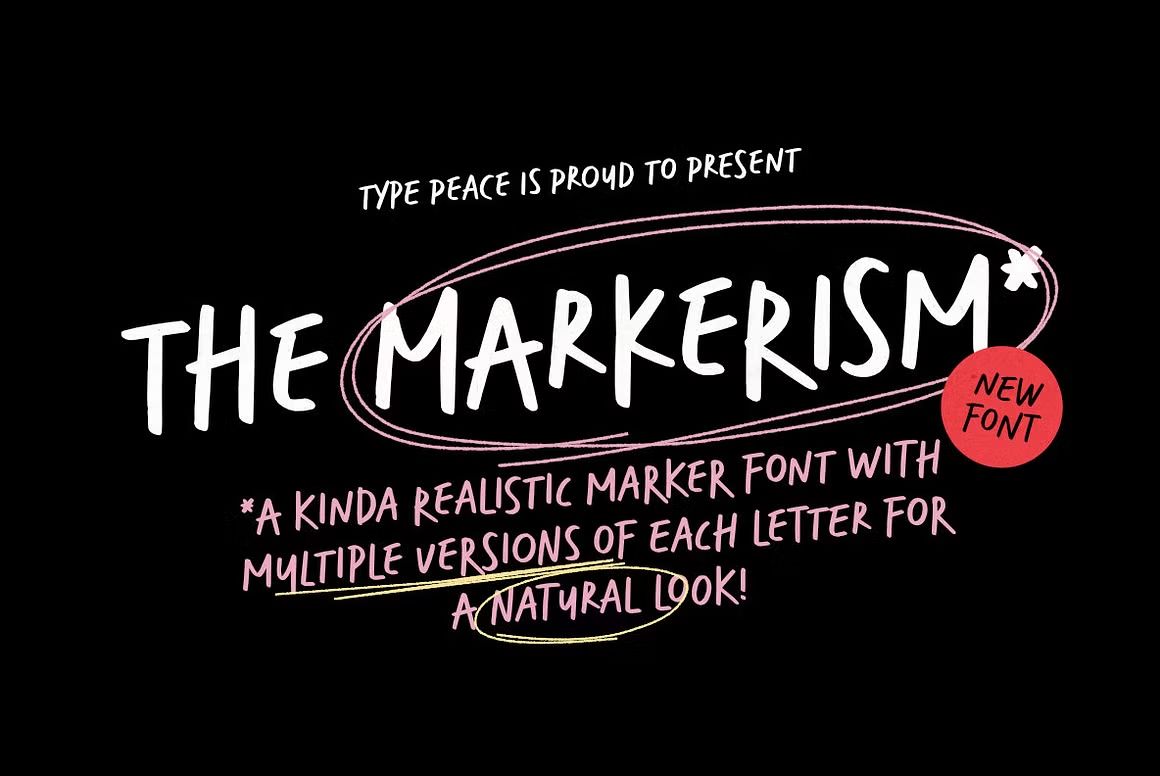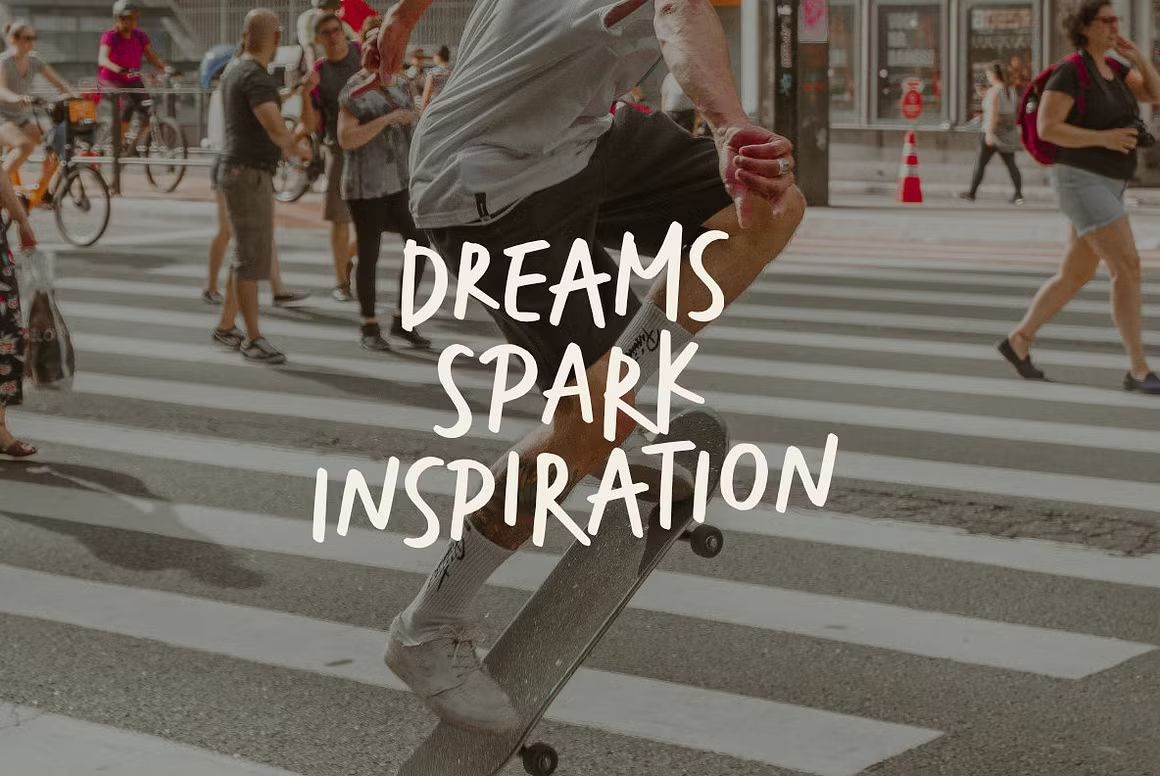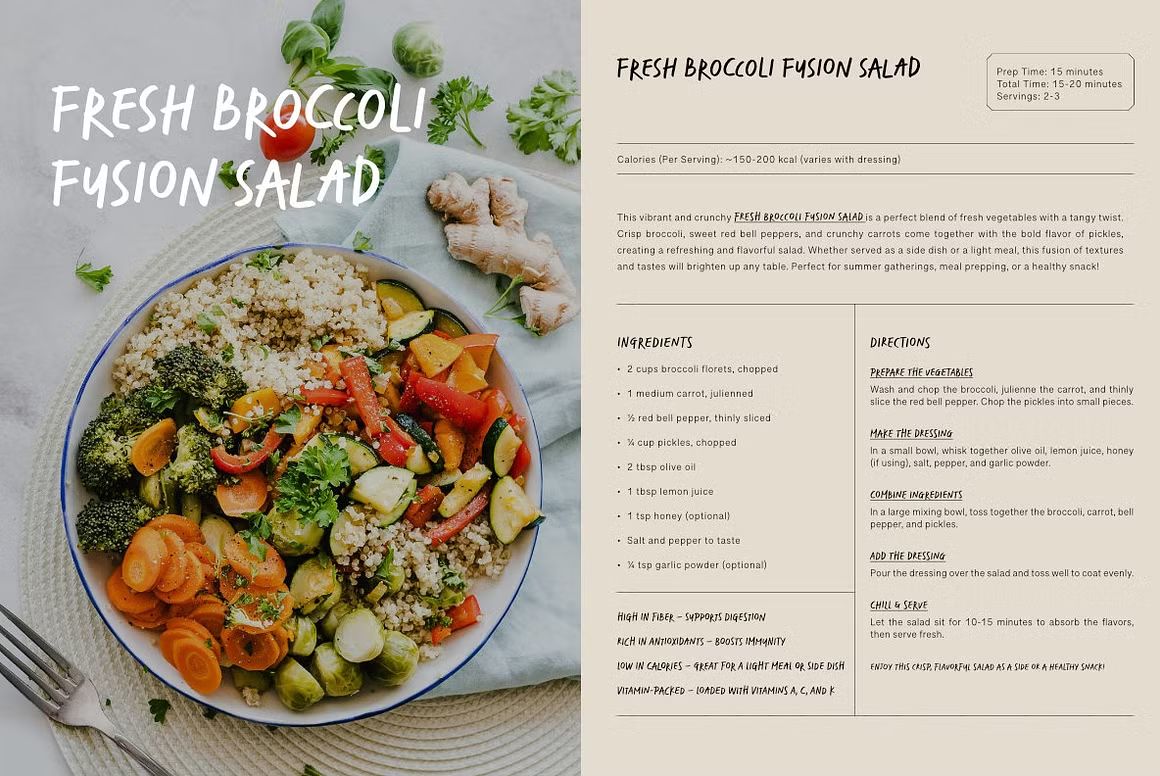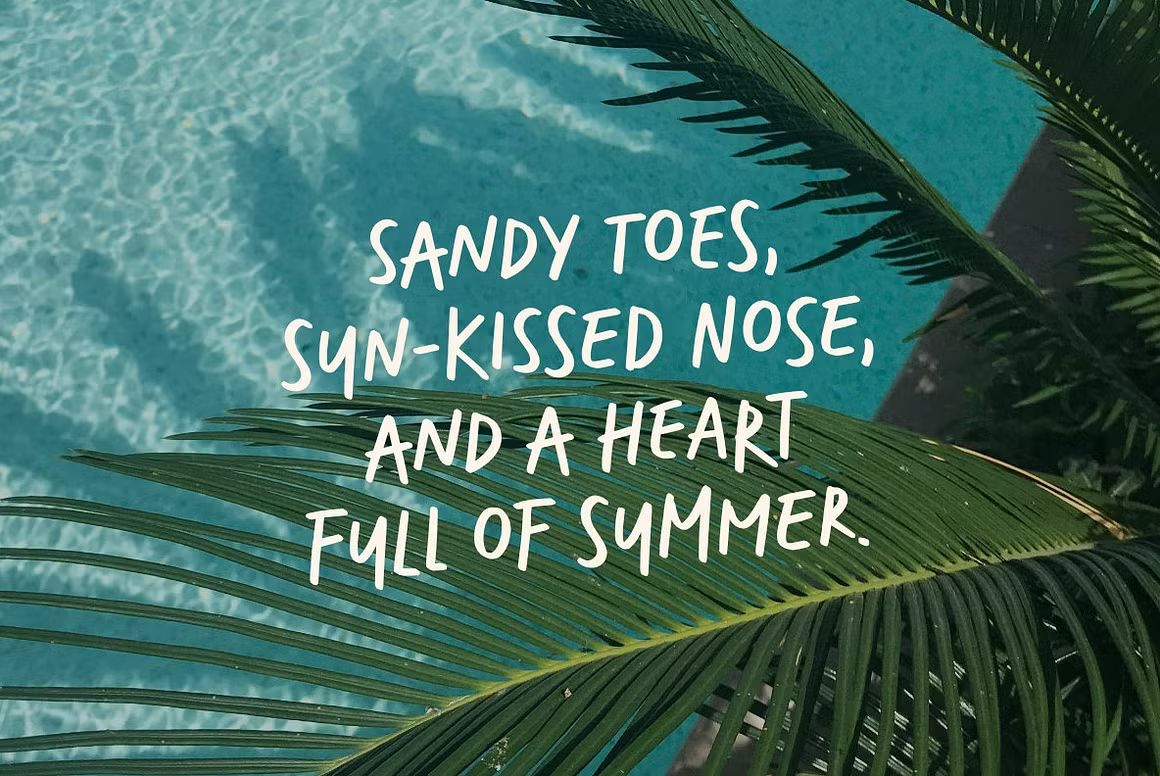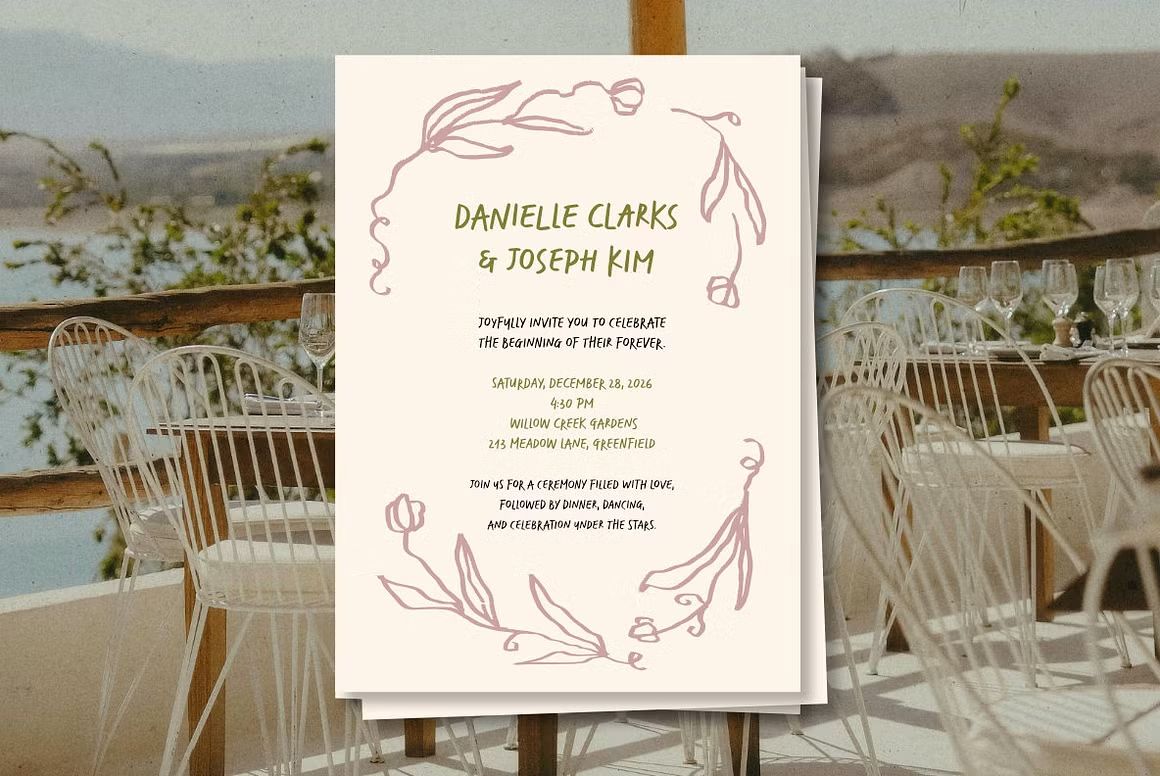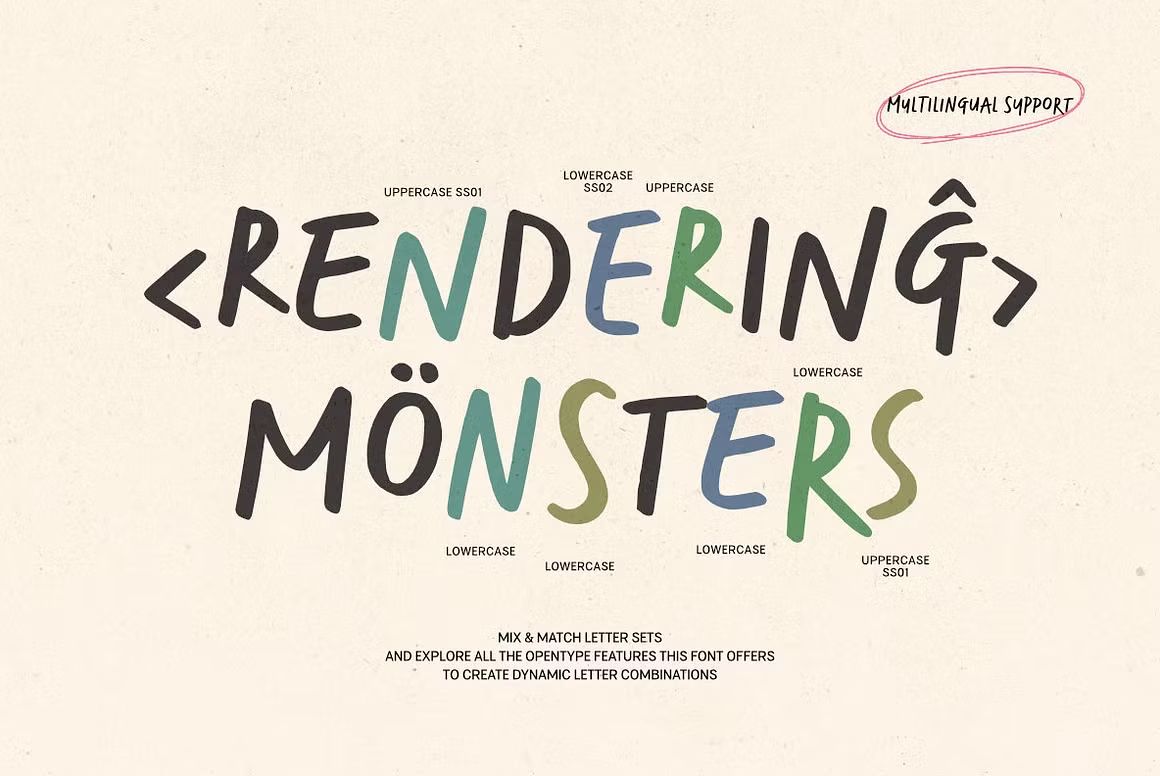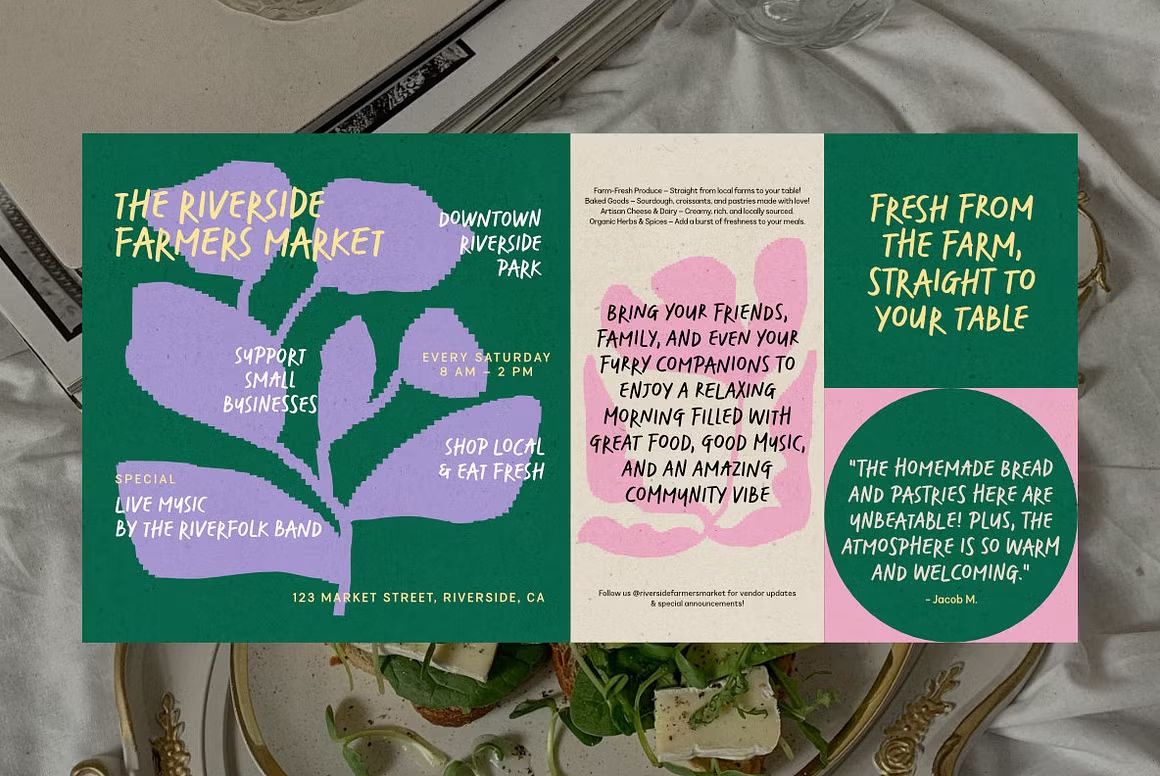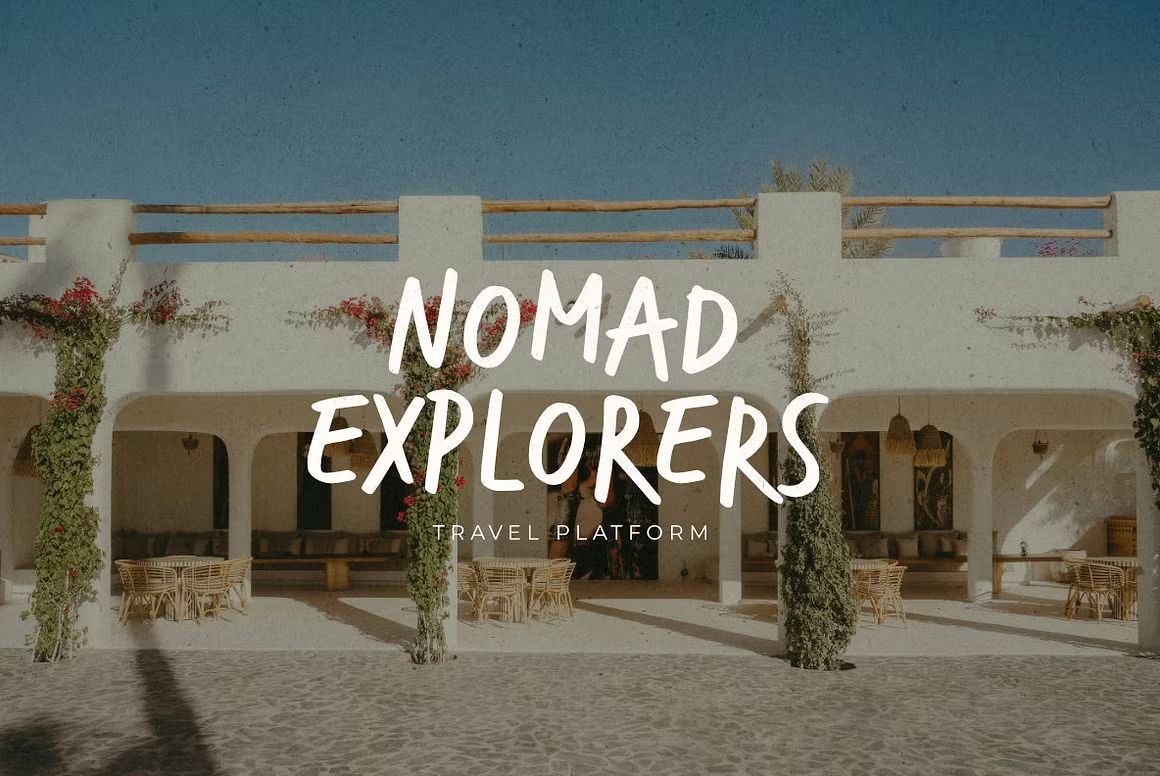
MARKERISM – Marker Font
MARKERISM adalah font bergaya marker yang bold dan ekspresif, cocok untuk desain poster, headline, sampul, dan proyek kreatif yang ingin tampil berani dan penuh karakter.
MARKERISM adalah font bergaya marker yang berani, ekspresif, dan penuh energi. Dengan goresan tebal dan tampilan seperti tulisan spidol asli, font ini ideal untuk menciptakan desain yang mencolok dan dinamis. Cocok digunakan untuk poster, headline, sampul, media sosial, atau proyek kreatif lain yang ingin menyampaikan pesan dengan kuat dan jelas.
Fitur unggulan:
• Gaya marker bold yang ekspresif dan penuh karakter
• Tampilan seperti tulisan tangan dengan spidol asli
• Cocok untuk poster, headline, sampul, dan media sosial
• Termasuk huruf besar, huruf kecil, angka, dan simbol
• Ideal untuk desain yang membutuhkan kesan kuat, kreatif, dan dinamis